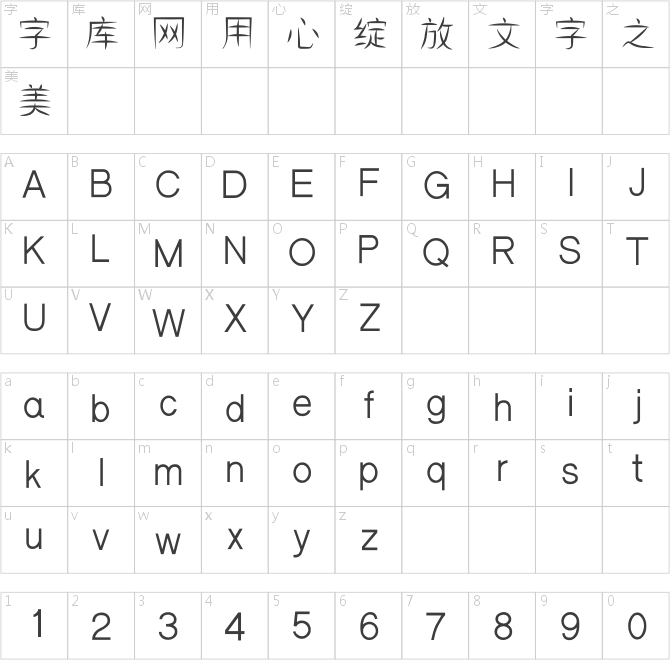
漢標(biāo)趙都體
漢標(biāo)趙都體字體字庫(kù)是一款讓人賞心悅目、百看不厭的中文字體,適合各類廣告和產(chǎn)品包裝設(shè)計(jì)應(yīng)用,字體大小2.03MB,格式為ttf字體,上傳用戶是漢標(biāo)文創(chuàng),作者/版權(quán)方為漢標(biāo)